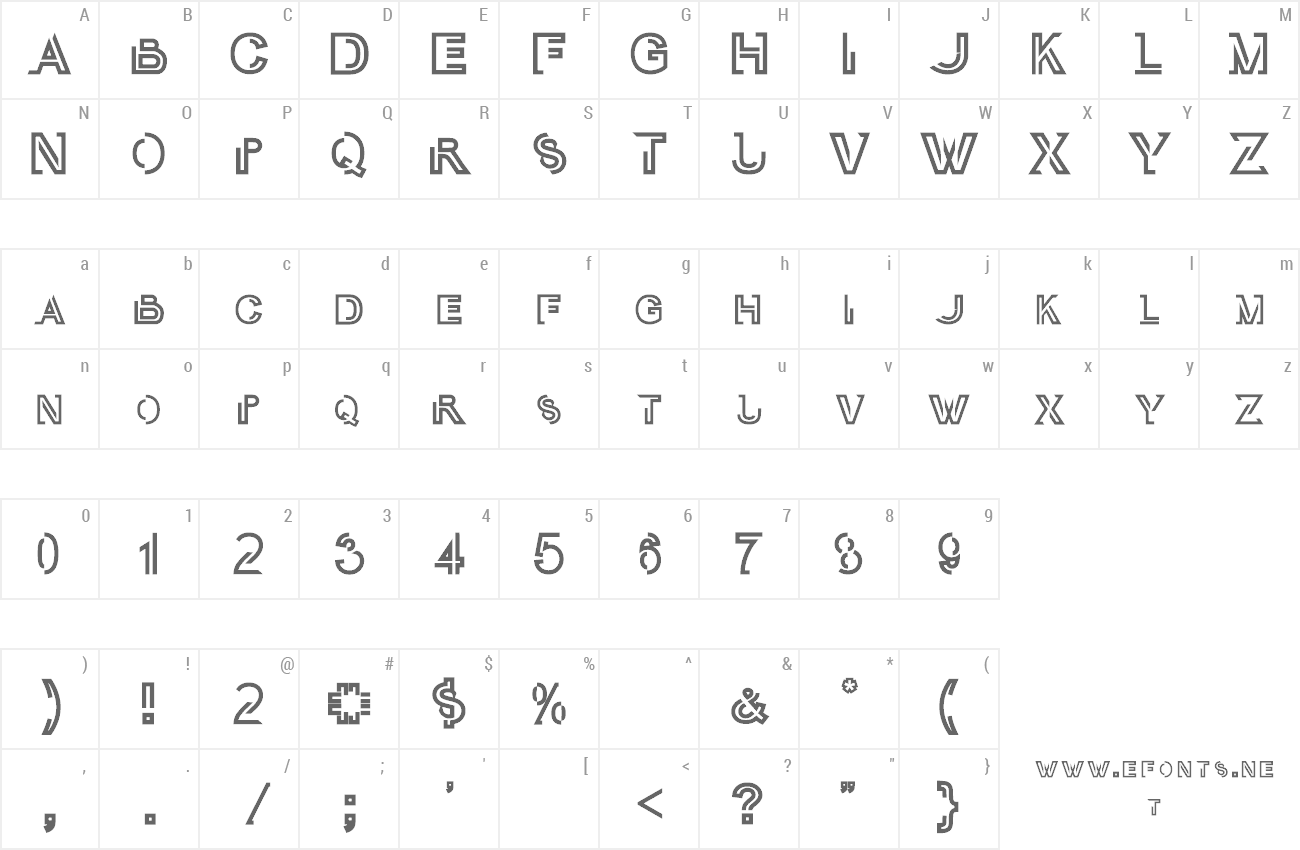
Preview and download Oubli Cap Font. Created by Jeremy Calli in Fancy Various styles with Demo license.
| Font name: | Oubli Cap |
| Author: | Jeremy Calli |
| Note by Jeremy Calli | |
| Le nom de la typographie rend hommage au documentaire de Franck Brudieux du même titre, je l'ai initialement inventé lors de la création de l'affiche qui devait l'illustrer. |